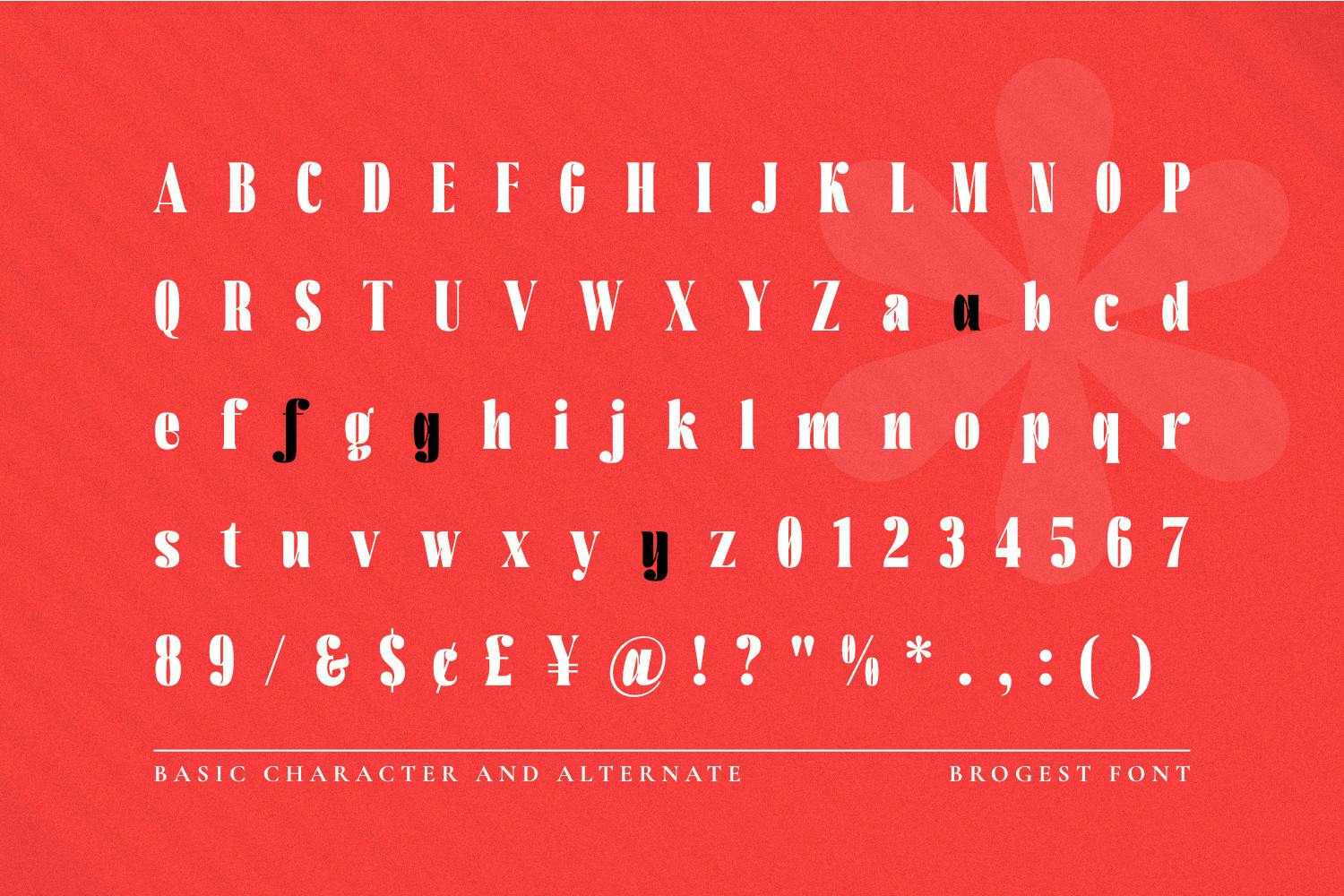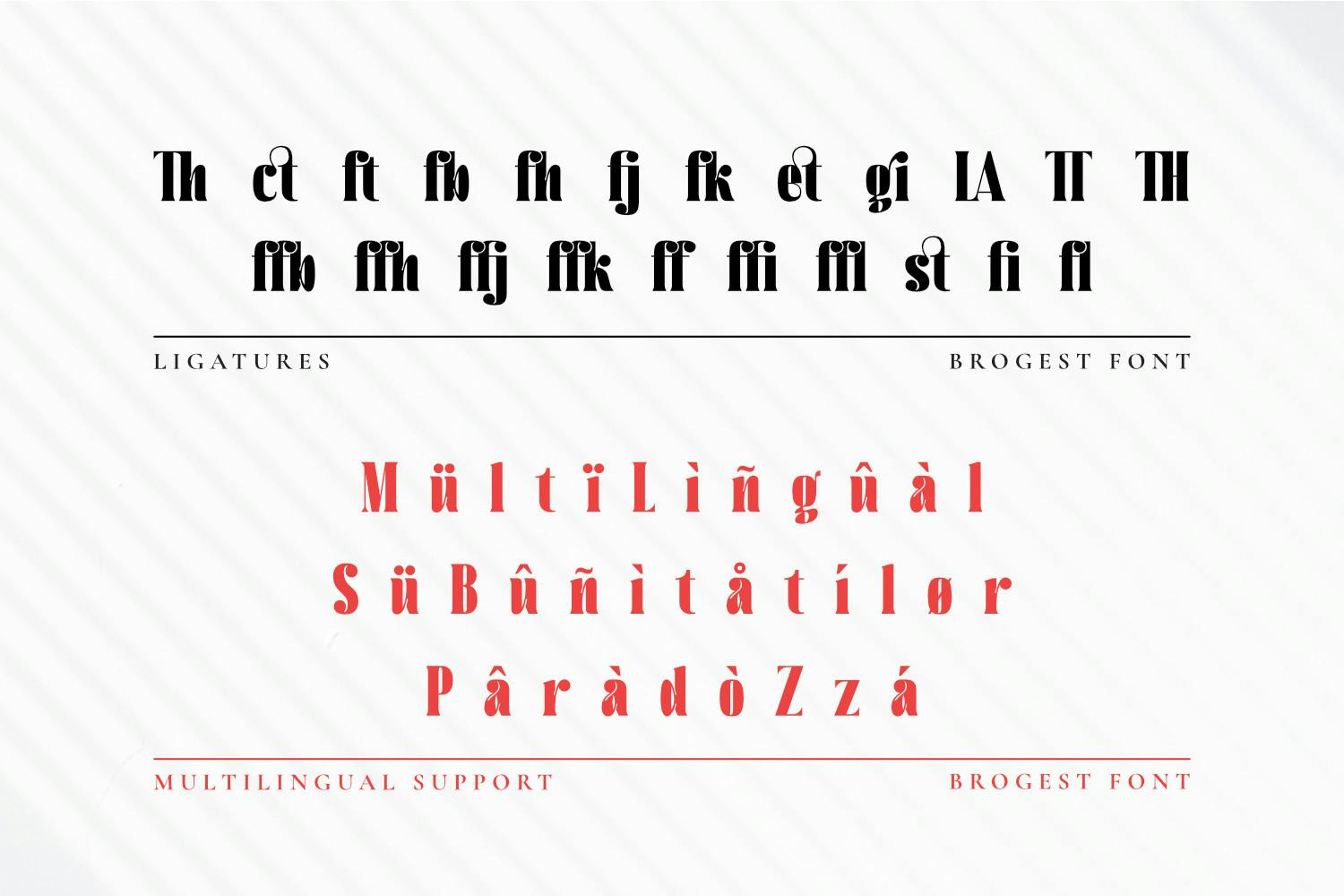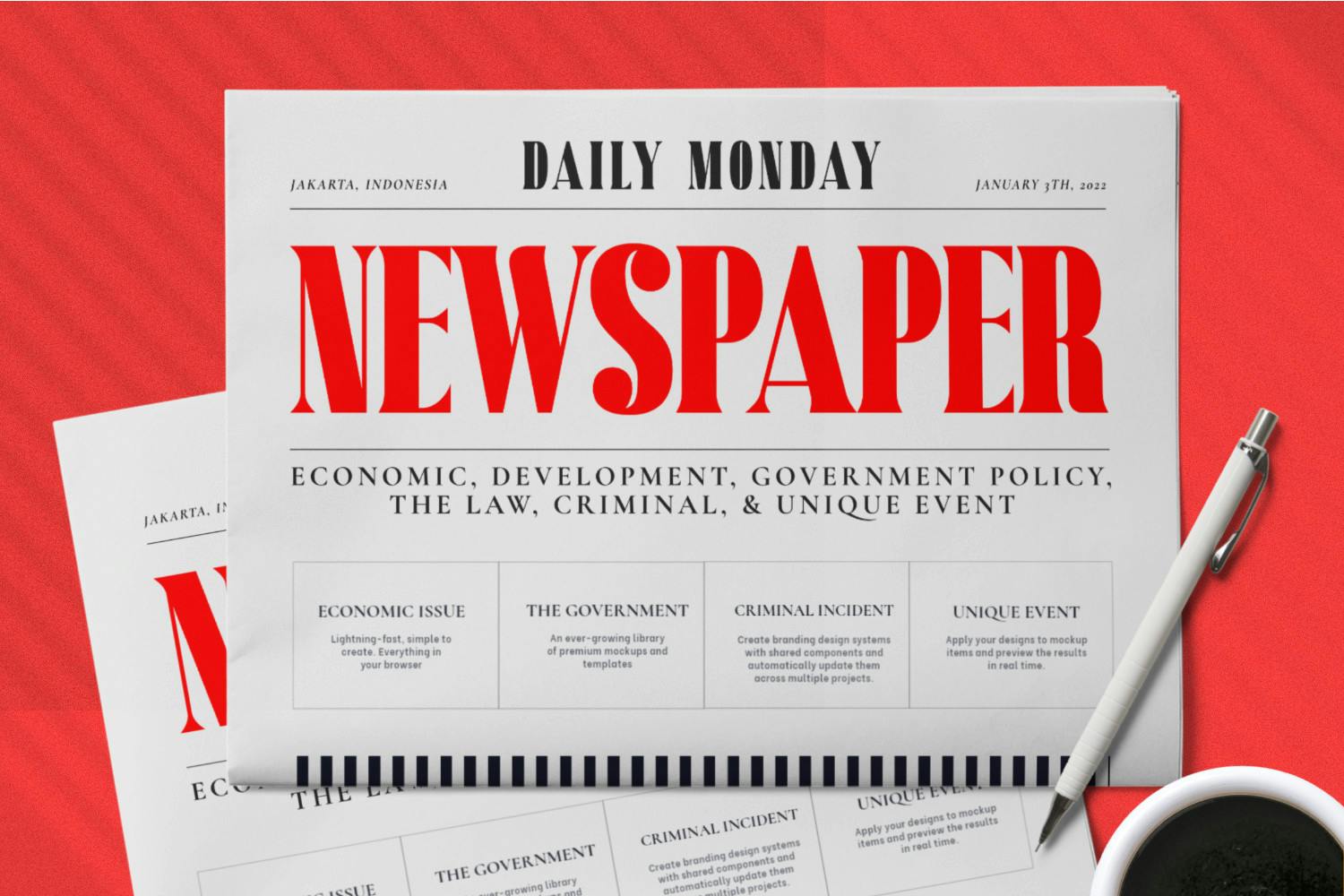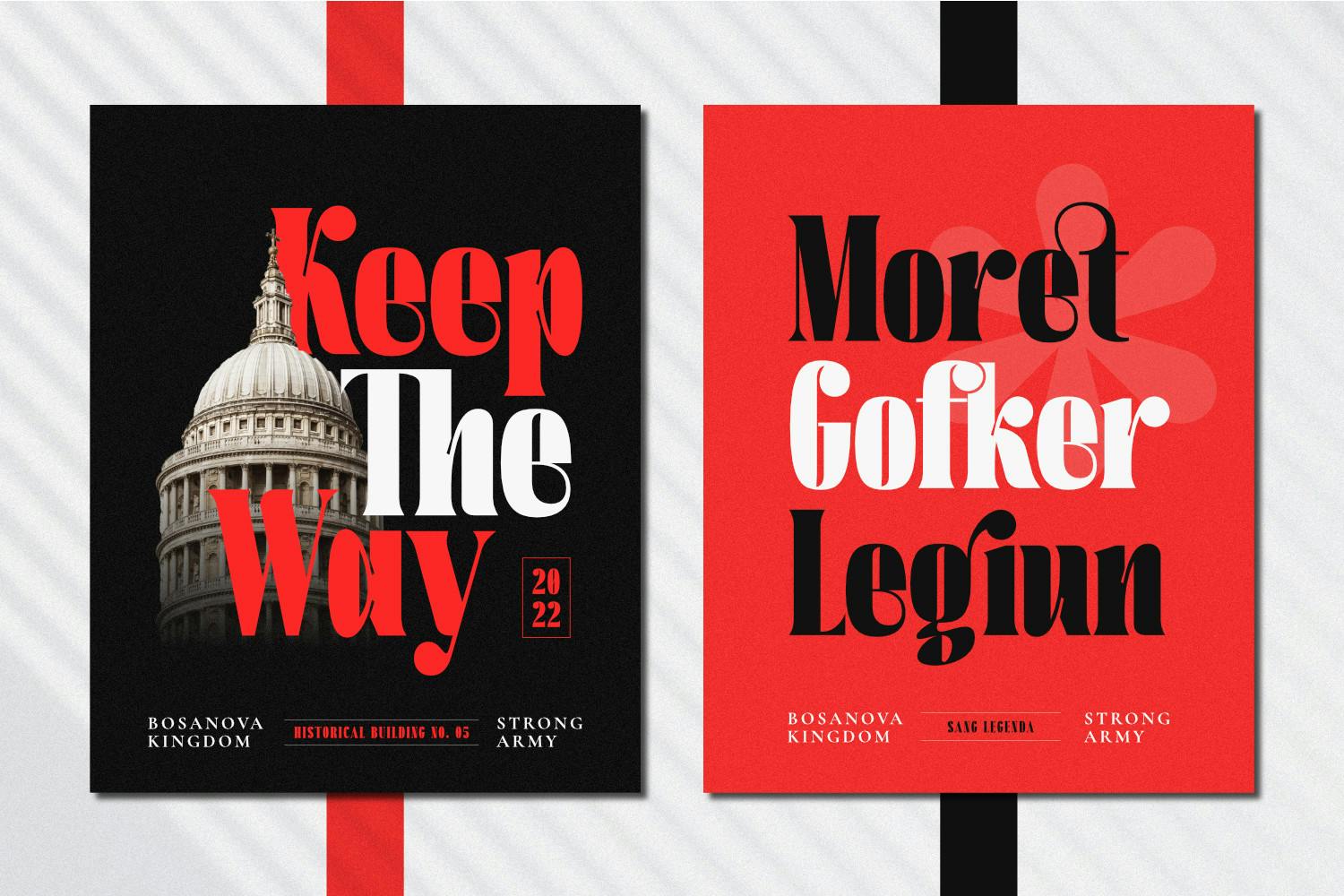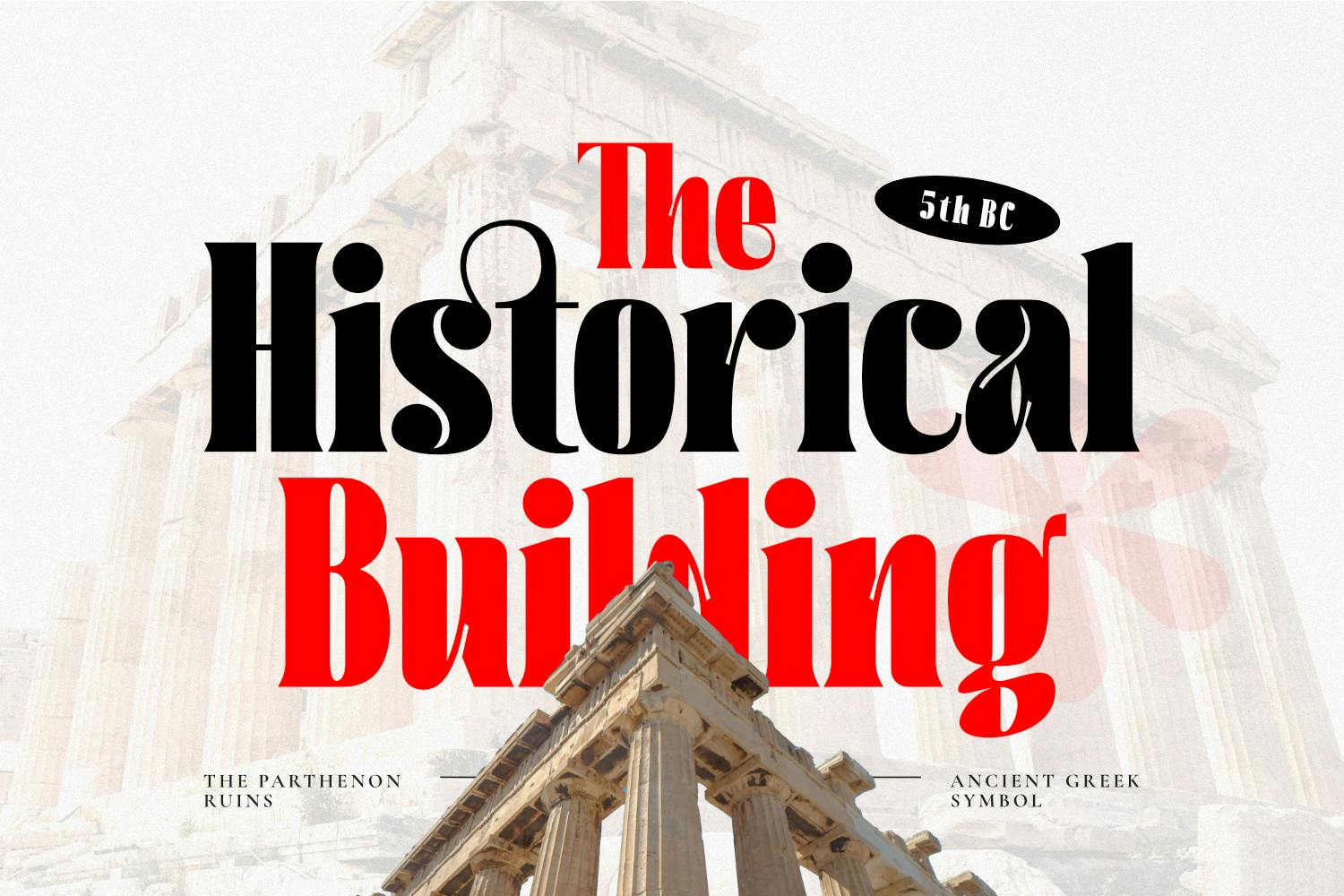
محصول فونت Brogest برای بسیاری از پروژههای شما مانند طراحی لوگو و برندینگ، عکاسی، دعوتنامهها، واترمارکها، تبلیغات، طراحی محصولات، لوازمالتحریر، طراحی عروسی، برچسبها، بستهبندی محصولات، رویدادهای ویژه و موارد دیگر بسیار مناسب است.